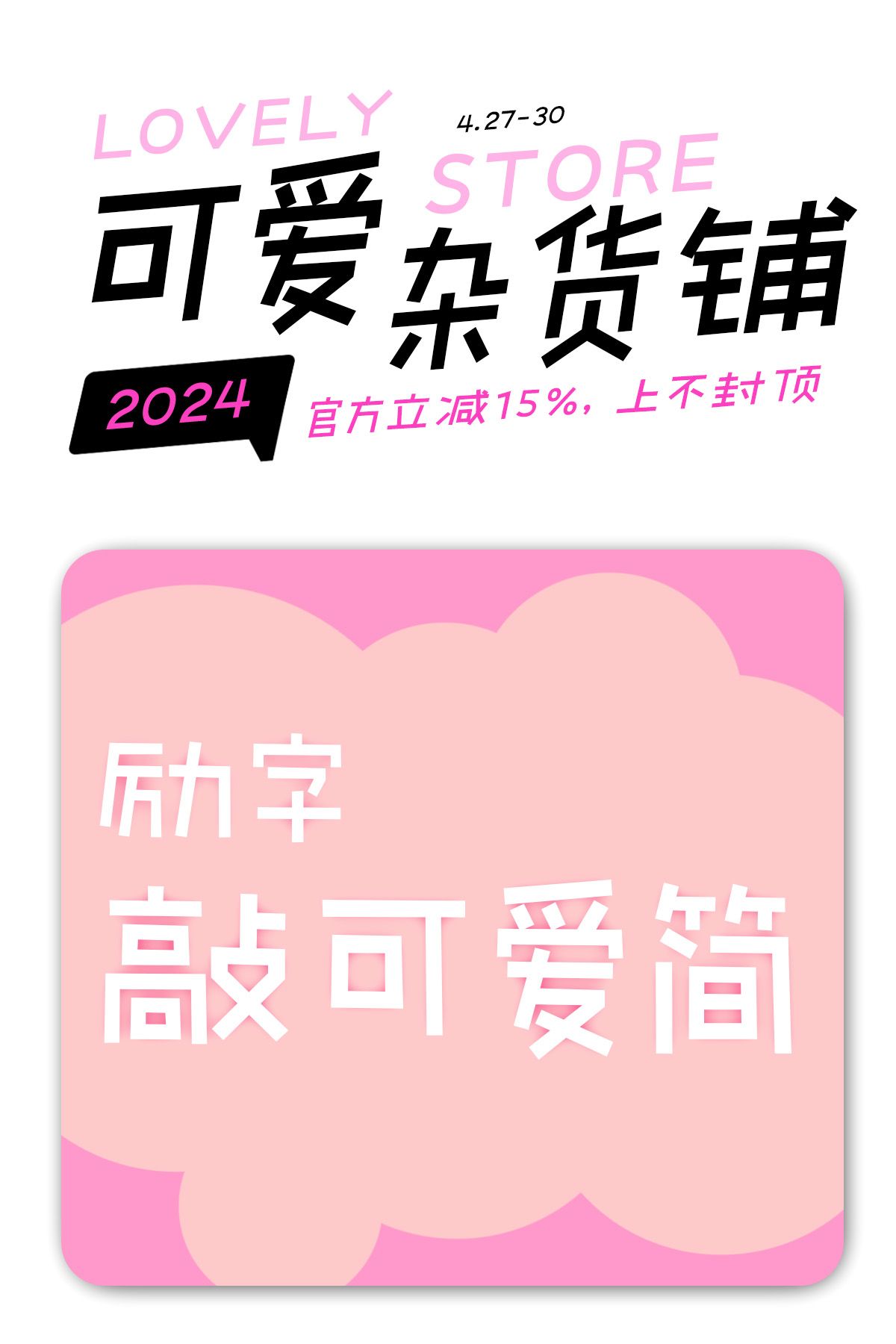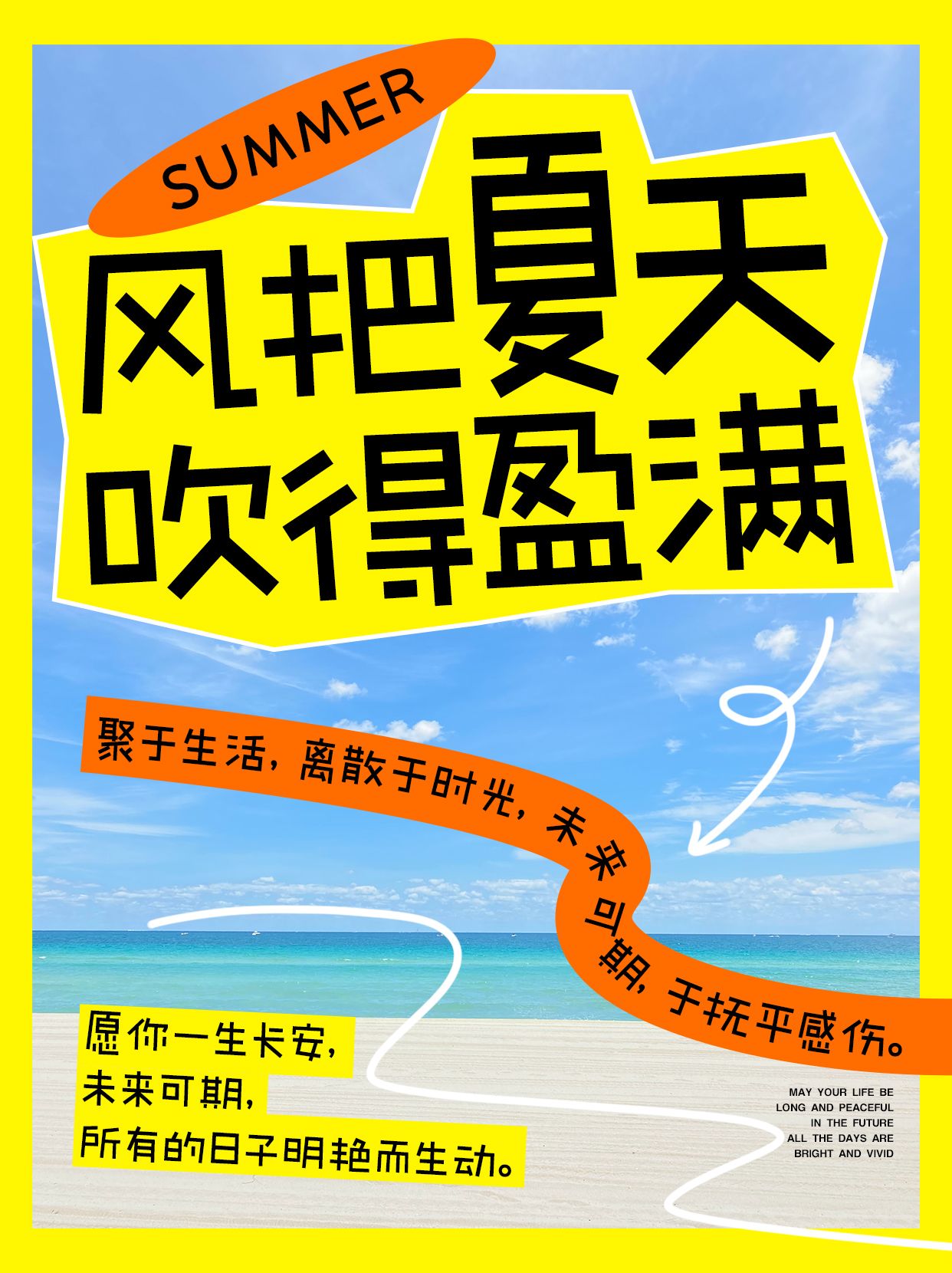
小红书封面字体推荐:打造吸睛封面的秘密武器
在小红书这个充满创意与个性的平台上,封面作为内容的“门面”,其重要性不言而喻。而字体作为封面设计的重要元素之一,更是能够直接影响到用户的点击率和阅读体验。那么,究竟哪些字体是打造吸睛封面的秘密武器呢?下面,就为大家推荐几款热门且实用的字体。
想要让你的小红书封面脱颖而出?不妨试试励字敲可爱简 中粗!这款字体结合了可爱与简约的设计,中粗的笔画既醒目又不失温柔,非常适合用于美食、成长故事等主题的封面。无论是个人分享还是产品推广,这款字体都能为你的内容增添一份独特的魅力,吸引更多用户的目光。
想要为小红书封面增添一份独特的艺术气息?字恋狂漫野 鸣风既有细腻的笔触,又有如鸣风般的力量感。用字恋狂漫野 鸣风制作封面,不仅能展现你的个性与品味,还能吸引更多目光。这款字体俏皮可爱,充满童趣。字恋狂漫野 鸣风非常适合用于萌宠、亲子、旅行等领域的封面设计,能够轻松吸引年轻用户的眼球。
励字磅礴简 超黑将磅礴的力量感与简洁的线条完美融合,超黑的字重更是显得尤为醒目。励字磅礴简 超黑笔画秀丽婉约,给人清丽的感觉,适合用于美妆、时尚、穿搭等领域的封面设计,能够营造出一种优雅、时尚的氛围。
手写字体因其独特的个性和温度感,近年来在封面制作上备受追捧。造字侠灵霄简繁 传神结合了传统与现代审美,简繁并存的设计、夸张地手写笔画能够迅速抓住用户的注意力,同时传达出深邃而传神的气息。无论是展示传统文化,还是分享现代生活,造字侠灵霄简繁 传神都能让你的封面脱颖而出。